Ce n’est jamais simple de raconter l’histoire d’un métier, voire d’un corpus comme la Typo. J’ai choisi délibérément deux focus: celui de l’épistémologie et celui des Héros de cette longue histoire. Il apparaît comme dans toute science de la connaissance qu’il est important de fixer les méthodes d’approches et d’analyse d’un corpus. Sans cela nous serions invariablement soumis à la seule méthode apprise à l’école élémentaire, la chronolgie. Or cette chronologie ne fonctionne qu’à moitié pour expliquer les évolutions. Comme le souligne Michel Wlassikoff il est important de se pencher sur les aspects politiques et sociales pour comprendre l’évolution des arts graphiques qui ne se suffisent pas d’explications technologiques comme le laisserait entendre d’autres points de vues déjà largement citées ici.
L’histoire de la Typographie se confond bien entendu avec l’histoire des tracés mais aussi des techniques de reproduction, auquel il faut ajouter bien entendu l’histoire permanente des transgressions. Cela donne une série de sinusoïdes progressifs et superposées sur un timeline qui va de 3000 ans avant JC jusqu’à nos jours.
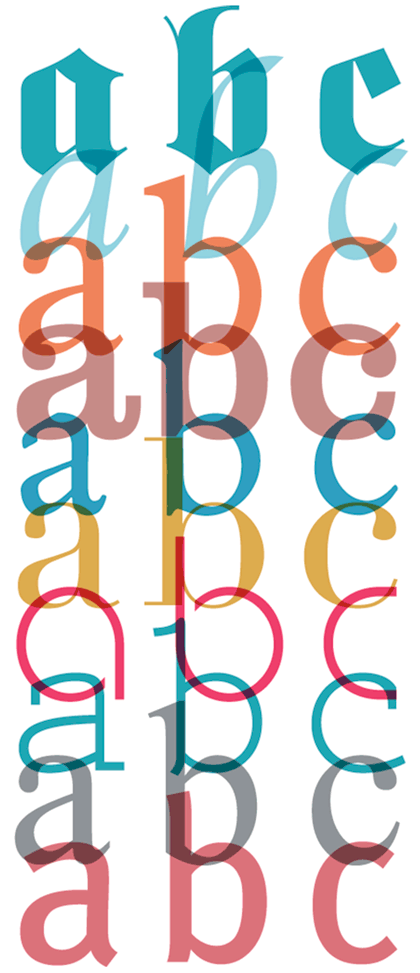
Ce panorama de la typographie à travers son histoire, lié à un angle savamment choisi d’acteurs majeurs du graphisme, fut un splendide voyage pour vos auditeurs !
La découverte de ces univers graphiques permet d’ouvrir le champ des possibles car il est infini. Tout le monde le sait, c’est tellement évident… pourtant, l’on oublie que nous bâtissons nous-même nos limites graphiques. Le graphisme, comme sans doute la typo, est un combat contre soi même… où l’on se doit de se libérer de ses propres limites. Et tout cela, avec une rigueur implacable. Il y a une complexité cérébrale palpable dans le travail de l’évidence graphique ;-) (en tous cas pour une apprentie!)